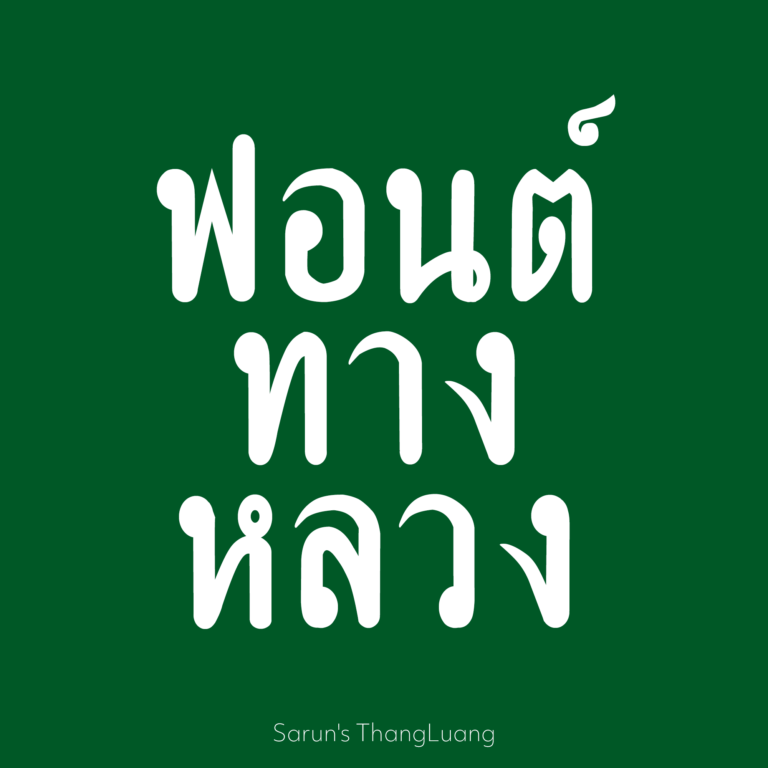
โคบาล (kho-ban)
ฟอนต์โคบาล เพิ่งทำเสร็จอยากปล่อยให้ใช้
ฟอนต์กาหล มีเฉพาะตัวอักษรภาษาไทย แจกฟรีครับ
ฟอนต์ลายมือที่คุ้นเคย จากหน้าหนังสือพิมพ์ไทยรัฐยุคเก่า
ฟอนต์จากหน้าปกซีดีพี่แจ้ชุด “ที่สุดสุนทราภรณ์” …ทำฟอนต์ 5 วัน ทำปก 2 เดือน
เป็นฟอนต์ที่ได้แรงบันดาลใจจากป้ายอุทยานสวรรค์ ขับรถผ่านไป ผ่านมาเห็นอยู่ทุกเช้าเย็น แต่ถามใครก็ไม่รู้ว่าฟอนต์อะไร เมื่ออยากได้ ก็ทำเองซิ
ฟอนต์เลียนแบบตัวหนังสือพิมพ์สมัยเก่าๆ อยากใช้แต่หาโหลดไม่ได้ เลยทำเอง
เวลาคิดไม่ออก มันก็คิดไม่ออกจริงๆ ว่าตัวต่อไปจะออกมาแบบไหน แต่เวลาคิดออก เหมือนมันอยู่ในหัว ไม่ต้องร่าง
ฟอนต์สไตส์เขียนพู่กันจีน ออกแบบ&เขียน โดย โกยัพ ศิลป์โกสีย์… ผมลอกเอามาทำฟอนต์
เป็นฟอนต์ที่ทำไว้นานแล้ว เอาโชว์ก็นานแล้ว ว่าจะปล่อยก็นานแล้ว แต่โชคร้ายตอนนั้นฮาร์ดดิสก์เจ๊งครับ แต่(อีกครั้ง) ฮาร์ดดิสก์ดีพระย่อมคุ้มครอง สามารถกู้ข้อมูลกลับมาได้(บางส่วน) ซึ่งหนึ่งในนั้นก็คือฟอนต์นี้นั่นเอง เอามาแก้ไขหน่อย เสร็จแล้วก็ปล่อยตามระเบียบ
เป็นฟอนต์ที่ทำเลียนแบบป้ายบอกทางตามถนนหนทาง (ที่เห็นกันจนชินตา แต่หาที่มาไม่ได้) ผมเลยทำเอาไว้ใช้เอง แต่เห็นว่ามีหลายๆคนถามถึงเลย ตัดสินใจเอามาปล่อย (ปล่อยนก ปล่อยปลายังได้บุญ นี่ปล่อยฟอนต์..มันน่าจะได้บ้าง นะผมว่า)
เป็นฟอนต์ที่แอบทำไว้ใช้เฉพาะกิจ ตอนแรกไม่มีมาตรการว่าจะเอามาปล่อย แต่เห็นว่ามีผู้ถามหากันมาก และยังไม่มีใครทำมาปล่อยก็เลยตัดสินใจปล่อย โปรดทราบ เนื่องจากเป็นฟอนต์เฉพาะกิจ จึงไม่มีฟอนต์ภาษาอังกฤษ (ภาษาอังกฤษจะเป็นฟอนต์จากเทมเพลตของท่านนายพล) มีเพียงภาษาไทย, สัญญลักษณ์ที่จำเป็นและตัวเลขเท่านั้น
เป็นฟอนต์ที่แอบทำไว้ใช้เฉพาะกิจ ตอนแรกไม่มีมาตรการว่าจะเอามาปล่อยแต่เห็นว่ามีผู้ถามหากันมากและยังไม่มี ใครทำมาปล่อยก็เลยตัดสินใจปล่อย โปรดทราบ เนื่องจากเป็นฟอนต์เฉพาะกิจ จึงไม่มีฟอนต์ภาษาอังกฤษ (ภาษาอังกฤษจะเป็นฟอนต์จากเทมเพลตของท่านนายพล) มีเพียงภาษาไทย, สัญลักษณ์ที่จำเป็น และตัวเลขเท่านั้น
เป็นฟอนต์ที่แอบทำไว้ใช้เฉพาะกิจ ตอนแรกไม่มีมาตรการว่าจะเอามาปล่อยแต่เห็นว่ามีผู้ถามหากันมากและยังไม่มี ใครทำมาปล่อยก็เลยตัดสินใจปล่อย โปรดทราบ เนื่องจากเป็นฟอนต์เฉพาะกิจ จึงไม่มีฟอนต์ภาษาอังกฤษ (ภาษาอังกฤษจะเป็นฟอนต์จากเทมเพลตของท่านนายพล) มีเพียงภาษาไทย, สัญญลักษณ์ที่จำเป็น และตัวเลขเท่านั้น
เป็นฟอนต์ที่แอบทำไว้ใช้เฉพาะกิจ ตอนแรกไม่มีมาตรการว่าจะเอามาปล่อย แต่เห็นว่ามีผู้ถามหากันมากและยังไม่มี ใครทำมาปล่อยก็เลยตัดสินใจปล่อย
[swfobj src=”http://www.f0nt.com/wp-content/uploads/2007/09/preview.swf” width=”450″ height=”500″] เป็นฟอนต์ที่ได้แรงบันดาลใจจากซองข้าวเกรียบ คิดว่าน่าเสียดายถ้าจะมีตัวอักษรแบบนี้อยู่แค่ 5-6 ตัว เลยมาขอคำปรึกษาและคำแนะนำจากเพื่อนๆ ชาว F0nt.com ค่อยๆปรับ ค่อยๆแก้ จนได้ฟอนต์ตัวใหม่ออกมาอย่างที่เห็น (โปรดทราบ : นี่ไม่ใช่ฟอนต์ที่ใช้บนซองข้าวเกรียบ เพียงแต่มีความคล้ายๆ เท่านั้น…) สุด ท้ายขอขอบคุณทุกคนที่ติชม แนะนำ ชี้แนว ฯลฯ จนฟอนต์นี้สำเร็จ เสร็จสิ้นก่อนกำหนด (ความจริง กะเอาไว้ว่า จะเสร็จประมาณ ลอยกระทง^^”) ขอบคุณครับ